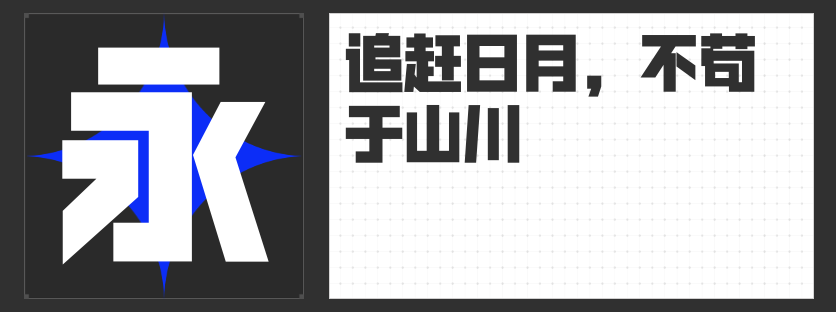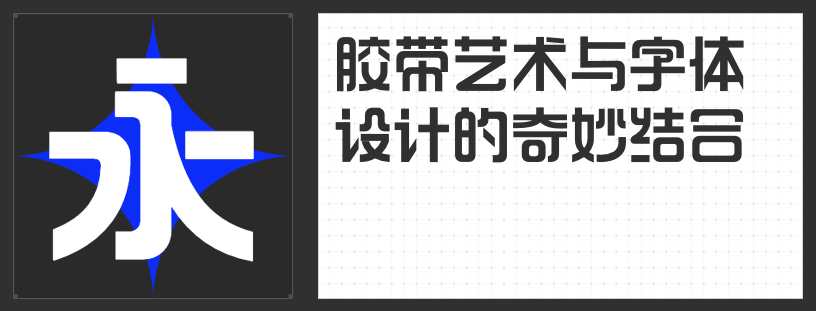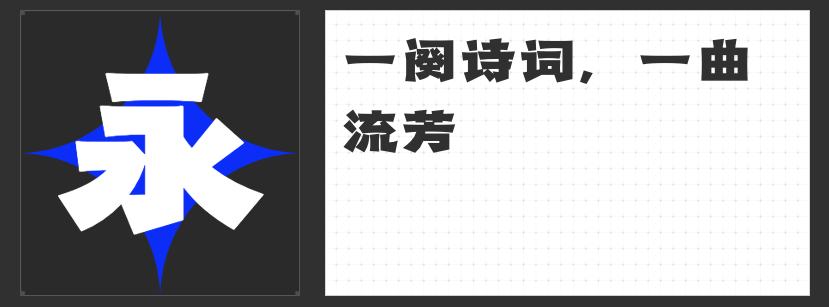
奥运荣耀,字体传情:四款精选字体献礼男子自由泳混合接力夺冠
随着泳池中水花四溅,男子自由泳混合接力赛的激烈角逐落下帷幕,冠军的荣耀瞬间点燃了全世界的激情。为了完美捕捉这份荣耀与辉煌,我们特别推荐四款字体,它们将成为奥运会宣传与海报设计中的点睛之笔。
这款字体以其厚重而不失流畅的线条,完美诠释了运动员们在水中的力量与速度。大黑的色调如同深邃的泳池,让人一眼就能感受到那份沉稳与坚定,是展现团队凝聚力与冠军风采的不二之选。
2.造字侠热辣隶简
这款字体巧妙地将传统隶书的韵味与现代简约风格相结合,为奥运宣传增添了一抹独特的文化气息。这款字体仿佛能够点燃观众心中的热情之火,让人在欣赏海报的同时,也能感受到那份对体育精神的热爱与敬仰。
励字开拓者简 超黑的设计如同运动员们冲刺时的身影,充满力量与速度感。它简洁而富有力量,能够瞬间抓住人们的眼球,将奥运赛场的紧张氛围与冠军的荣耀瞬间定格在海报之上。
这款字体以其细腻的线条和温馨的色彩,为奥运宣传带来了一抹柔和的色彩。它如同运动员们赛后绽放的笑容,传递出运动带来的快乐与满足。在展现竞技精神的同时,也不忘提醒我们享受运动带来的纯粹快乐。
这四款字体各具特色,无论是用于奥运会宣传还是海报设计,都能为作品增添独特的魅力与韵味。它们不仅是文字的载体,更是情感的传递者,让我们共同期待在未来的奥运赛场上,见证更多荣耀与辉煌的瞬间。